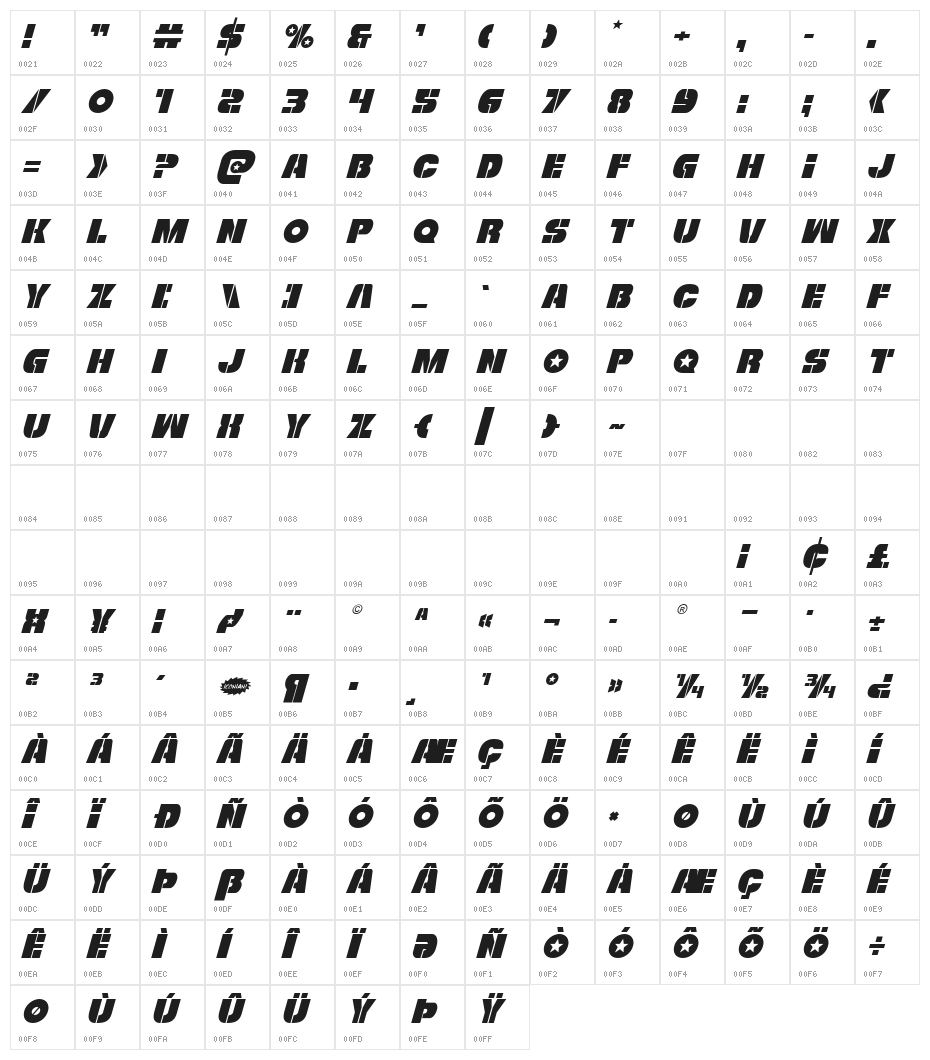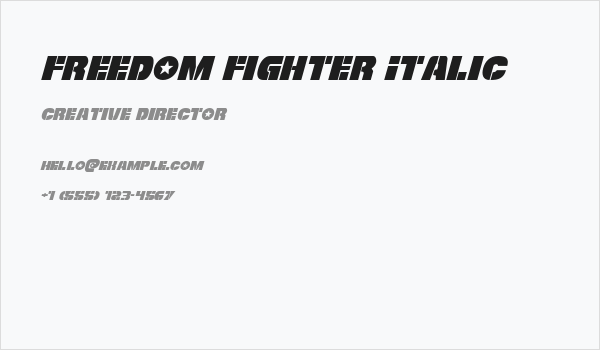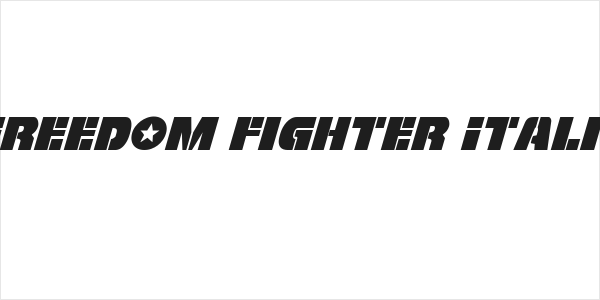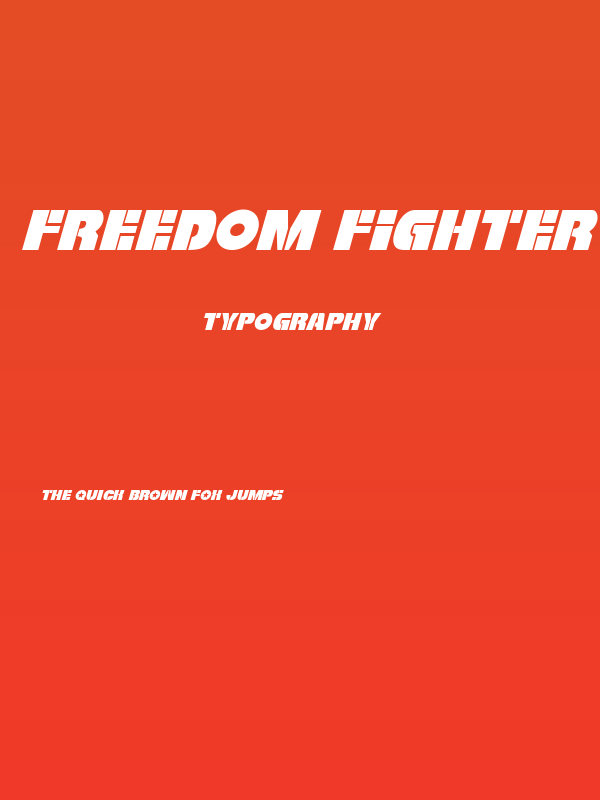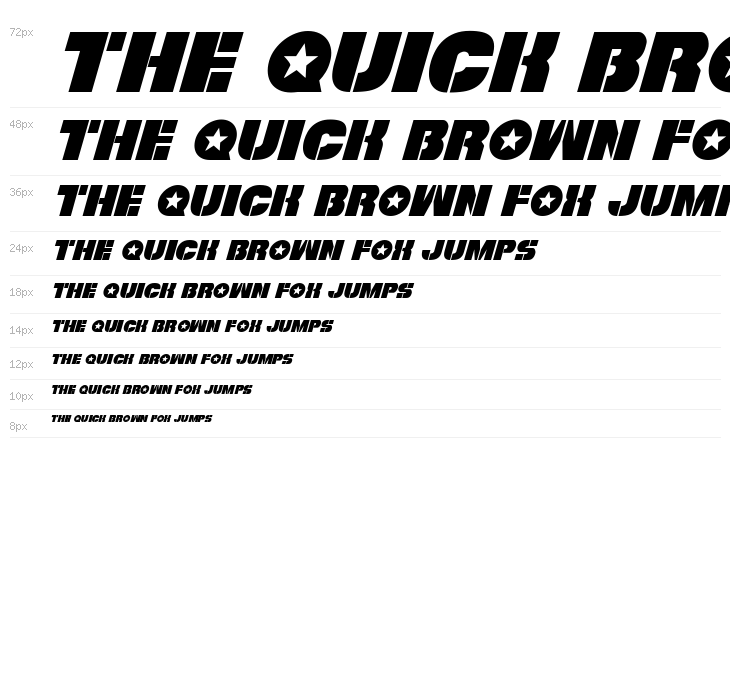
Freedom Fighter Italic Font
| Proyectos propuestos | Ideal for posters, video game titles, action movie covers, and branding that requires a strong, impactful presence. |